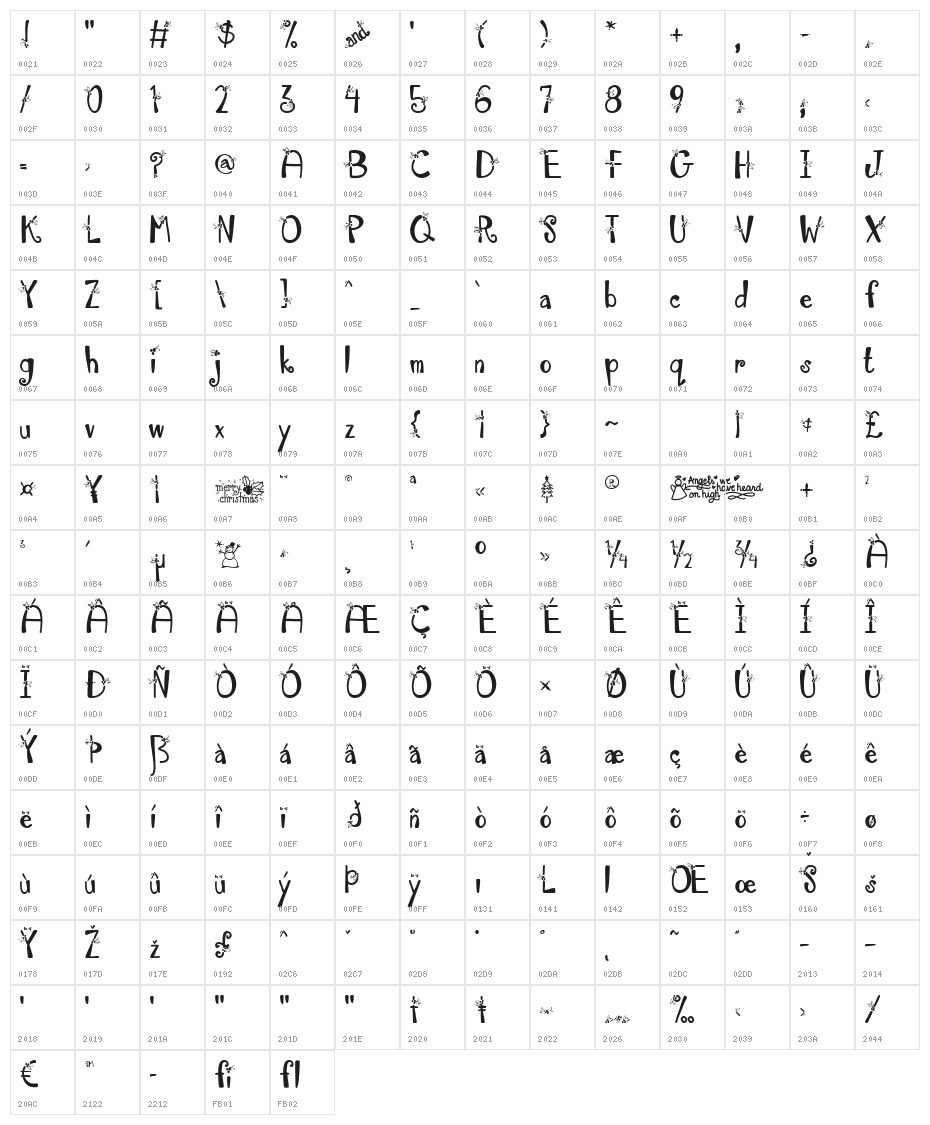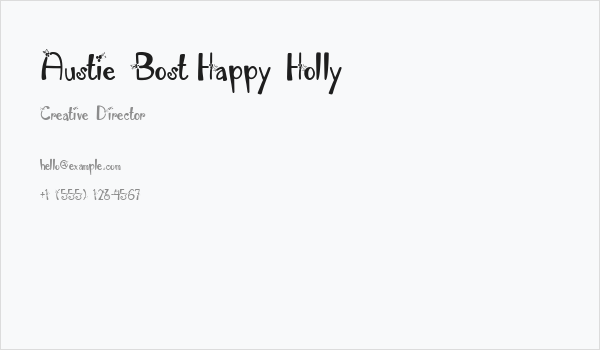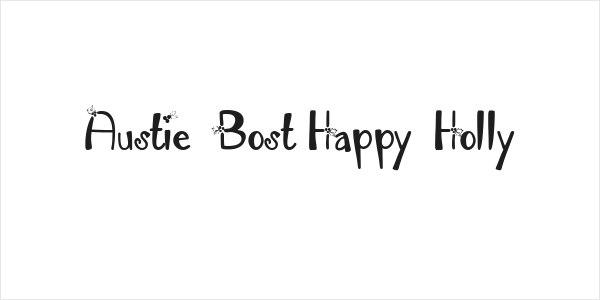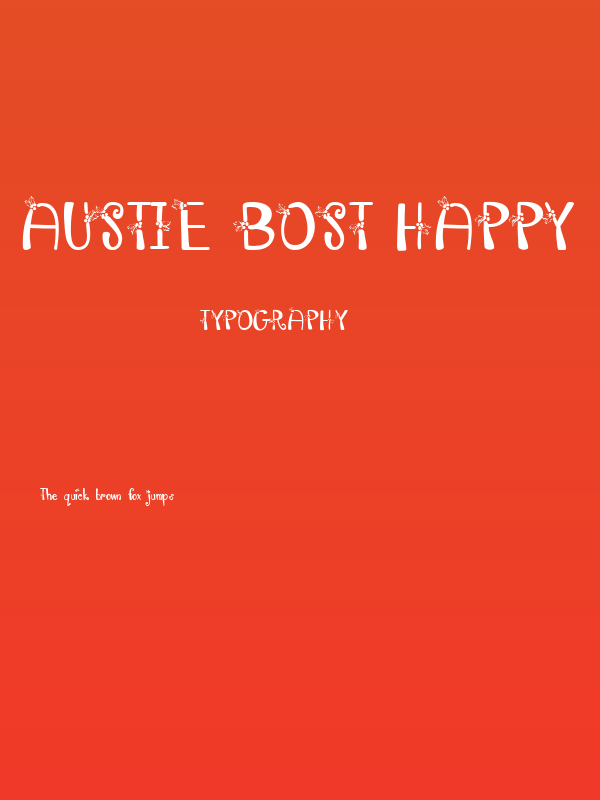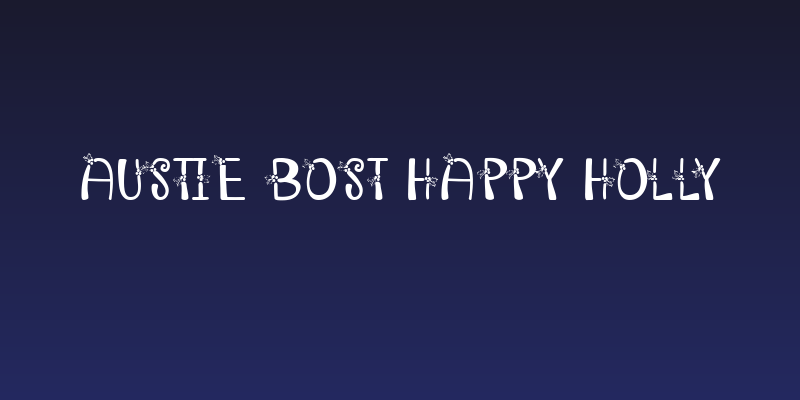
Austie Bost Happy Holly Font
| Anwendungsfall | Headlines, Logos, Invitations |
| Vorgeschlagene Projekte | Ideal for holiday cards, festive invitations, playful branding, and creative posters. |